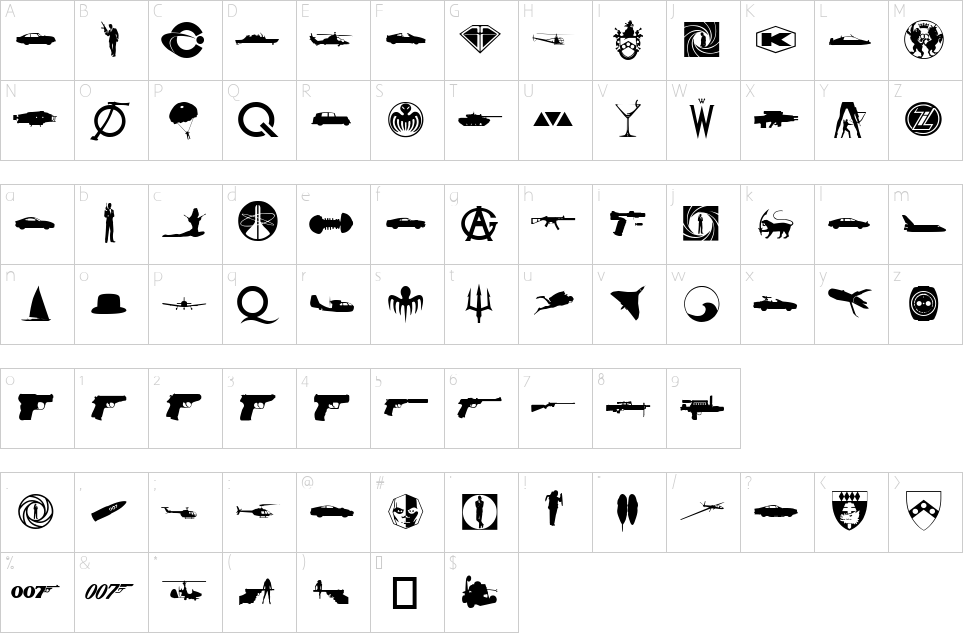
Aqui está uma descrição curta para a página de download da font ‘James Bond 007’ que segue as instruções fornecidas: Descubra a elegância sofisticada dos heróis do espionaje com o famoso código sigiloso James Bond 007. Esta font foi criada por Glyphcraft, um designer de letras talentosíssimo. James Bond 007 oferece uma experiência visual aguçada e vibrante para quem aprecia os temas de filmes icônicos como a série dos Heróis do Espionaje. Aproveite esta font gratuita que já foi baixada por 826 usuários, um número que testem prima-se o interesse e a popularidade desta font em sites e projetos de gráficos. Se você procura uma maneira criativa de adicionar um toque de classe ao seu design digital, este é seu texto. Sinta-se à vontade para experimentar esta font única e imortalizada na cultura do cinema!